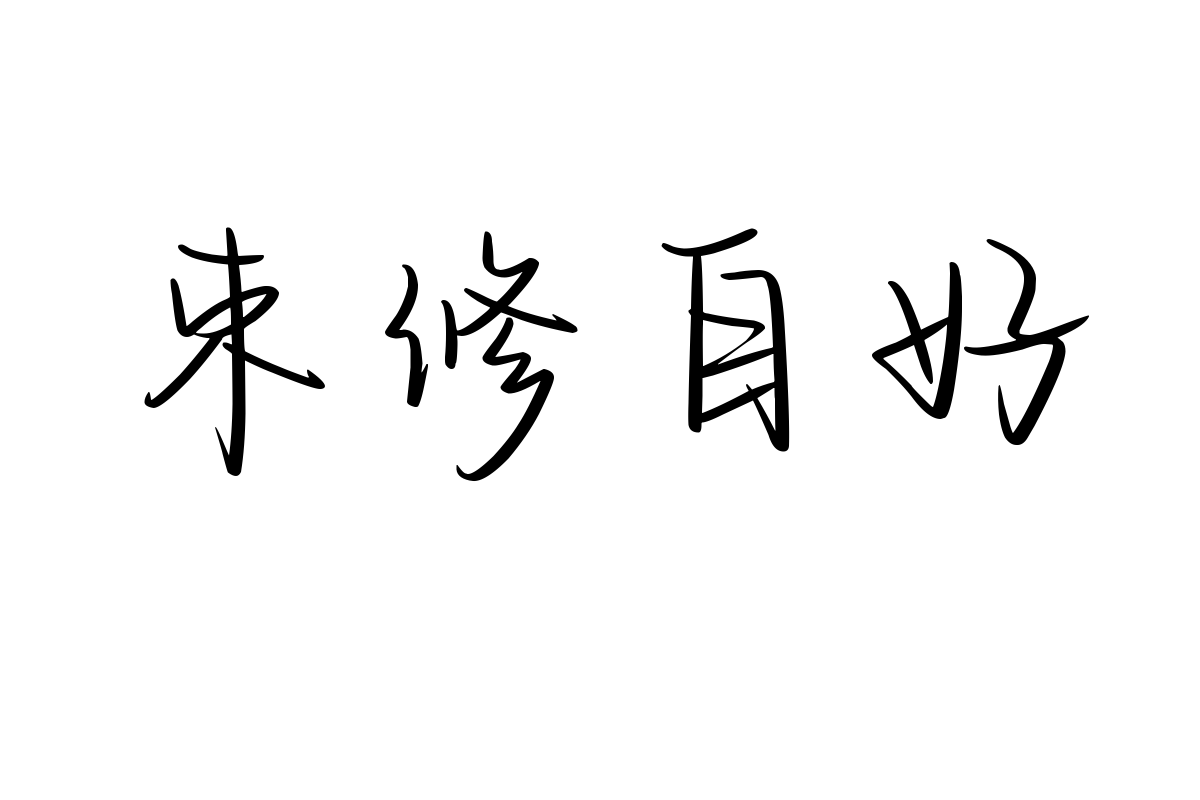
也字工厂文德斯体是一款具有独特风格的字体。它的设计灵感来源于德国著名诗人文德斯,因此得名“文德斯体”。这款字体的特点在于其独特的字形结构,使得每一个字母都充满了艺术感和个性。
也字工厂文德斯体的笔画粗细适中,线条流畅自然,给人一种优雅而不失力量的感觉。它的每个字母都有自己独特的风格,既有传统的韵味,又不失现代的时尚感。这使得这款字体在使用时能够给人留下深刻的印象,同时也能够很好地融入各种场合和场景中。
总的来说,也字工厂文德斯体是一款非常独特且具有艺术感的字体。它不仅能够为文字增添美感,还能够提升整体的设计效果和视觉冲击力。无论是用于书籍、杂志还是网页设计,都能够展现出独特的魅力和风格。